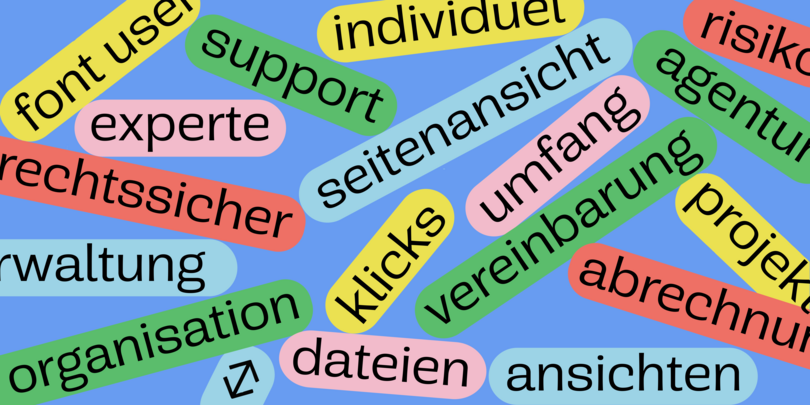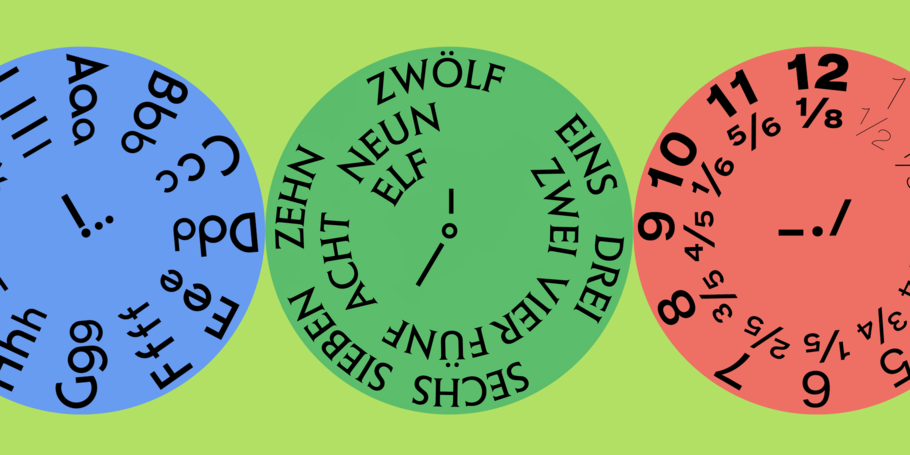
Gestalten ohne Hürden: Fonts richtig lizenzieren.
Bild, Farbe, Musik, Schrift – diese vier Bausteine sind für die Erstellung von digitalen Inhalten und Marketingkampagnen essenziell. Wie bei Aschenputtel gibt es jedoch nur eine magische Schrift, die zu einem bestimmten Projekt oder einer bestimmten Kampagne genau passt. Wenn ein Marketing- oder Kreativteam die seiner Ansicht nach perfekte Schrift gefunden hat, die eine Botschaft am besten transportiert, scheint alles andere wie von selbst zu laufen – mit Ausnahme der Lizenzfragen.
Stellen wir uns kurz vor, wie ein Kreativteam stundenlang an der Erstellung einer Kampagne gearbeitet hat, die wirklich überzeugt, die für mehrere Kanäle optimiert wurde und die in der Branche neue Maßstäbe setzen könnte. In mühevoller Kleinstarbeit wurde die perfekte, auf alle Ziele abgestimmte Schrift gefunden und die Kampagne gestartet.
Nach der Veröffentlichung der ersten Motive erhält die Rechtsabteilung der beworbenen Marke Post von einem Schrifthaus mit dem Hinweis, dass die Kampagne bzw. die Anzeigen eine Schrift enthalten, die möglicherweise nicht ordnungsgemäß lizenziert wurde. Das Legal-Team muss einen Aktionsplan erstellen und in den nächsten Stunden mit dem Font-Hersteller, dem Kreativteam, der Unternehmensleitung und der Abteilung für Öffentlichkeitsarbeit kommunizieren. Das geplante Media-Budget wird unversehens für die Überarbeitung der Kampagne sowie für eventuelle Schadensersatzzahlungen an das Schriftenhaus zurückgestellt. Im schlimmsten Fall spricht sich die juristische Auseinandersetzung in den sozialen Medien herum und schadet sowohl dem Ruf der Marke als auch dem der Agentur. Die Kampagne muss aus den digitalen Plattformen wie auch aus den analogen Kontaktpunkten zurückgezogen werden, weil es keine Lizenzen für diese Art der Verwendung gibt. Die Teamleiter müssen die Verantwortung für den Fehler übernehmen, das Unternehmen verliert eine Menge Geld.
Warum überhaupt in Schrift investieren?
Die Schrift einer Marke oder eines Unternehmens ist die Basis für seine visuelle Identität und der Schlüssel für eine gute Marketingkampagne. Große Fußball-Bundesliga-Clubs wie Bayern München oder Borussia Dortmund haben mit Bayern Sans bzw. FF DIN seit Jahren ihre eigenen Schriften (das gilt übrigens nicht nur für die großen Vereine, sondern auch für kleinere Clubs wie Mainz 05 oder Hertha BSC). Coca-Cola hat eine weltbekannte Schrift, die sich wunderbar von dem leuchtend roten Hintergrund abhebt, während sich Walt Disney ein unverwechselbares Logo mit einem geschwungenen „D“ gönnt. Über die Logos hinaus hilft Schrift den Marken, eine klare Identität für ihre Produkte zu etablieren – man denke nur an M&M’s oder Fritz-Kola. Die Werbesprüche mancher Kampagnen wie zum Beispiel Die Milch macht’s haben sich aufgrund ihrer visuellen Kraft in die Köpfe ganzer Generationen eingebrannt, selbst wenn die Kampagne seit Jahrzehnten nicht mehr läuft.
Unternehmen, die auf verschiedenen Plattformen werben oder sich auf diese verlassen, müssen die Kampagnen-Fonts für jedes Medium überprüfen. Manche Fonts geben auf Instagram ein gutes Bild ab, funktionieren aber auf YouTube nicht richtig. Andere Schriften entfalten ihre ganze Kraft auf Großflächenplakaten, verlieren aber an Wirkung, wenn sie über digitale oder mobile Kanäle ausgespielt werden. Erfolgreiche Werbekampagnen oder Projekte für den öffentlichen Raum erfordern spezifische Schriftschnitte, um eine Botschaft einwandfrei wiederzugeben.
Professionelle Schriftanbieter haben alles
Foundrys, also Unternehmen, die Schriften erstellen, vertreiben die Fonts gemäß Lizenzen, die den Nutzer:innen bestimmte Verwendungszwecke gestatten. Kommerzielle Lizenzen kommen bei Marketingkampagnen ins Spiel, bei kommerziell veröffentlichten digitalen Inhalten, bei Printanzeigen in Zeitungen oder Zeitschriften sowie bei der Verwendung auf Plakatwänden und Websites oder in Apps. Daneben können die Fonts jederzeit für persönliche Projekte oder interne Veranstaltungen genutzt werden, zum Beispiel für die Ankündigung einer Büroparty oder im Rahmen einer PowerPoint-Präsentation für ein internes Meeting.
Ein großes Problem bei der Font-Lizenzierung kann der Endbenutzer-Lizenzvertrag (EULA) sein, den die Benutzer wie beim Kauf jeder anderen Software auch beim Kauf einer Schrift akzeptieren. Es gibt Millionen von Schriften im Netz, und jede von ihnen wird mit einer Lizenzvereinbarung geliefert. Rechtsabteilungen verbringen zig Stunden damit, jedes einzelne Agreement zu prüfen, um Urheberrechtsklagen zu vermeiden. Wenn jemand die Nutzungsbedingungen für einen Font falsch versteht oder ignoriert, können die Folgen kostspielig werden.
Aus Fehlern lernen: Die häufigsten Probleme bei der Lizenzierung von Schriften
Designer, Rechtsabteilungen und Führungskräfte wissen natürlich ganz genau, wie wichtig es ist, das Kleingedruckte in Verträgen und Lizenzvereinbarungen genau zu studieren. Doch selbst in großen Unternehmen ist es bereits vorgekommen, dass Marketingmaterialien, Anzeigen, Kampagnen und sogar Produkte zurückgerufen werden mussten, weil man zu spät festgestellt hat, dass eine Schrift falsch eingesetzt wurde.
Was passiert, wenn man eine Schrift ohne Lizenz verwendet? Für Unternehmen aus der Unterhaltungsindustrie kann ein solcher Fehler Schadensersatzzahlungen in Millionenhöhe verursachen, ganz zu schweigen von den Kosten für Neukreationen, verschwendete Werbegelder und juristische Auseinandersetzungen. Produkte mit einer nicht oder nicht ordnungsgemäß lizenzierten Schrift müssen aus den Regalen genommen und in den Giftschrank gelegt werden, wo sie nie wieder das Licht der Welt erblicken.
Designer sind nicht die einzigen, denen diese Thematik Kopfschmerzen bereitet. Auch für die Abteilung für Öffentlichkeitsarbeit, die den Ruf eines Unternehmens verteidigen muss, können sich solche Fälle, je nach Ausmaß der Zweckentfremdung, zu einem Alptraum entwickeln. Ein beliebter US-Online-Marktplatz wurde kürzlich in den Medien des Schrift-Diebstahls beschuldigt: Das Wort „Diebstahl“ und der Markenname in einer Schlagzeile, das kommt nirgendwo gut an. Zwar hat in großen Unternehmen sicher niemand die Absicht, Fonts zu stehlen, weshalb solche Behauptungen nicht nur unglücklich formuliert, sondern schlicht falsch sind. Es ist dann aber zu spät: Derartige Anschuldigungen hinterlassen in der Öffentlichkeit und den Suchmaschinen dauerhaft Spuren.
In all diesen Fällen hätte es die genannten Probleme nie gegeben, wenn die verwendeten Fonts korrekt lizenziert worden wären – und zwar zu einem Betrag, der einem Bruchteil der durch den Fehler entstandenen Kosten entspricht. Vor ein paar Jahren musste ein großes Unternehmen fast 3 Millionen € Schadensersatz für die falsche Nutzung einer Schrift zahlen, deren Lizenzierung rund 200 € gekostet hätte.
Fazit